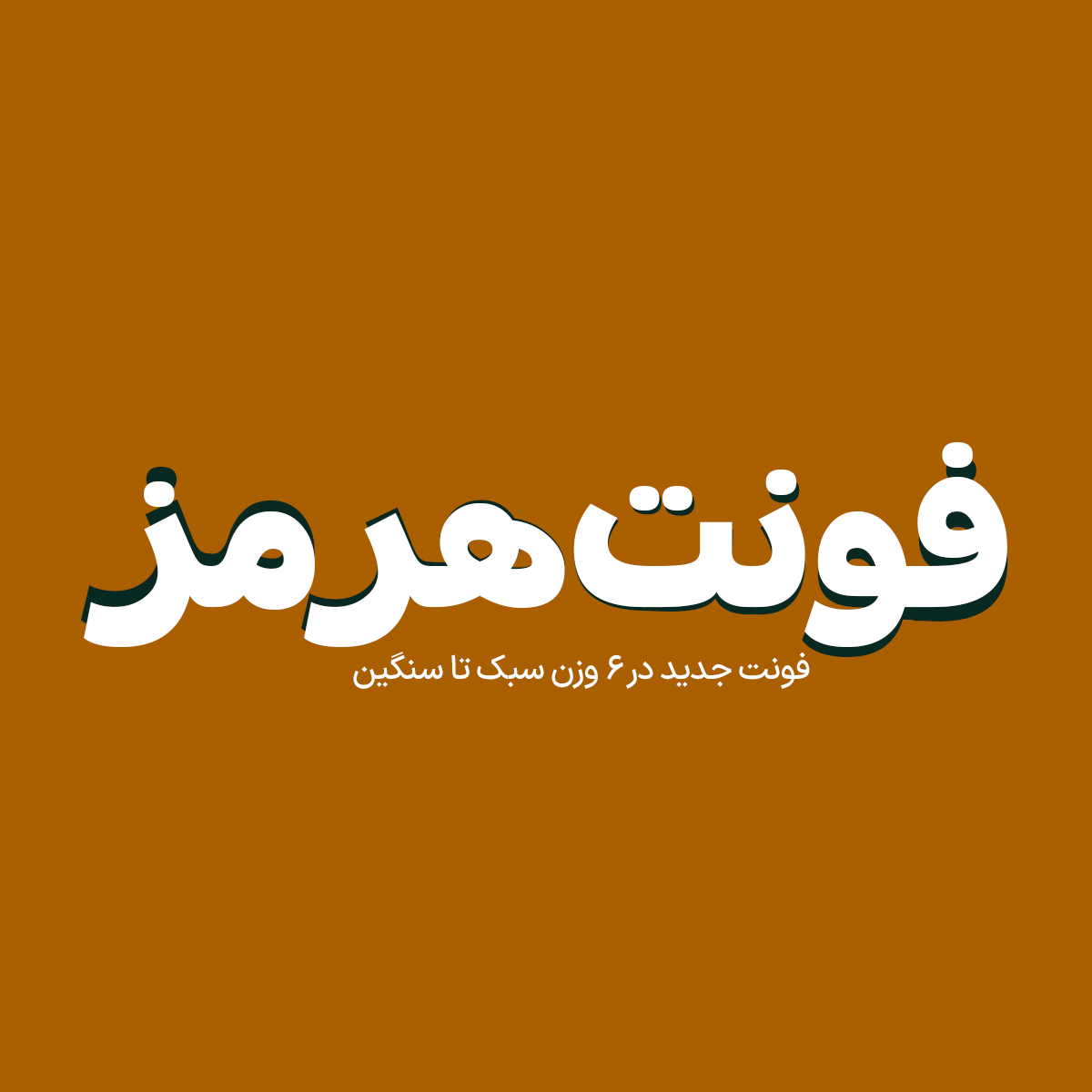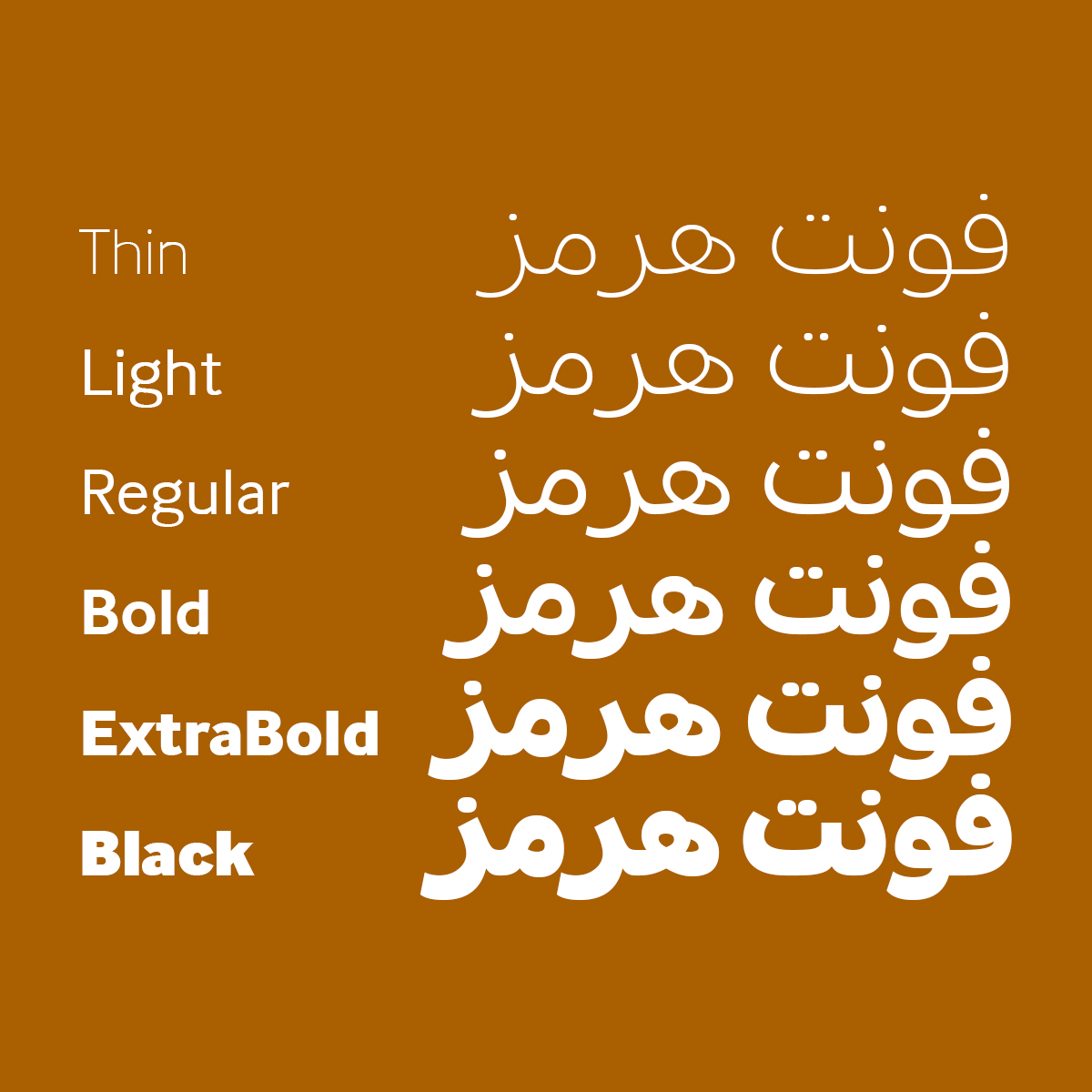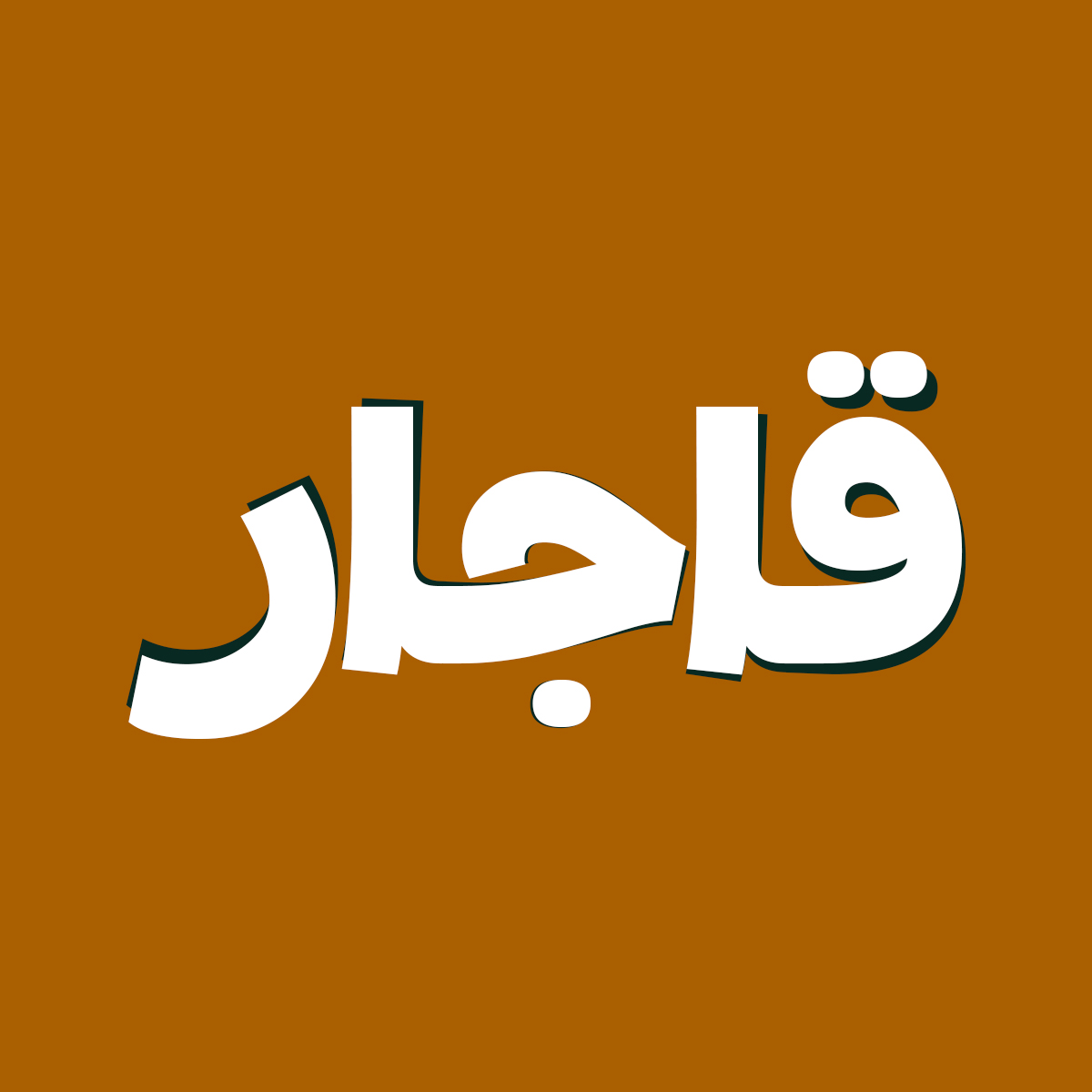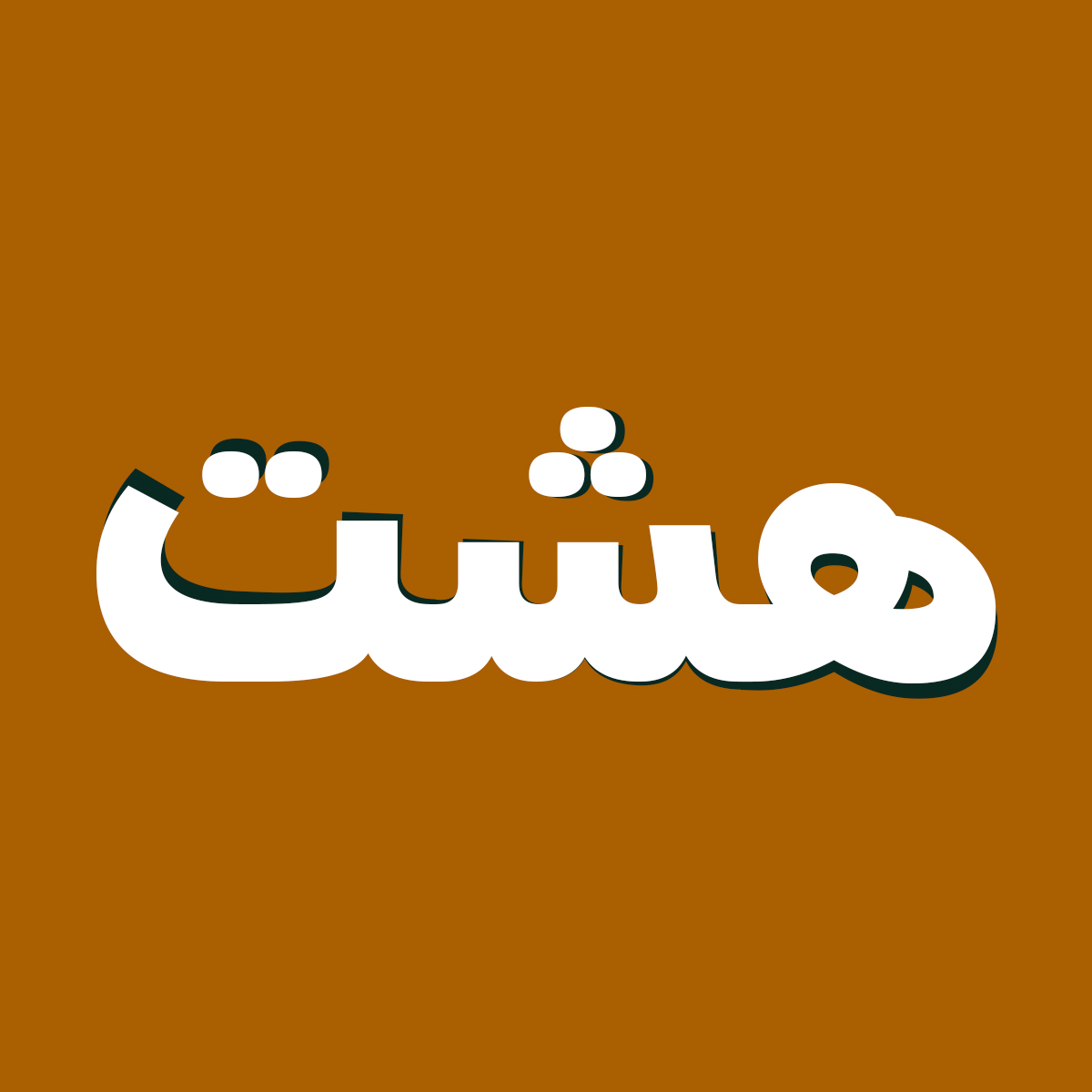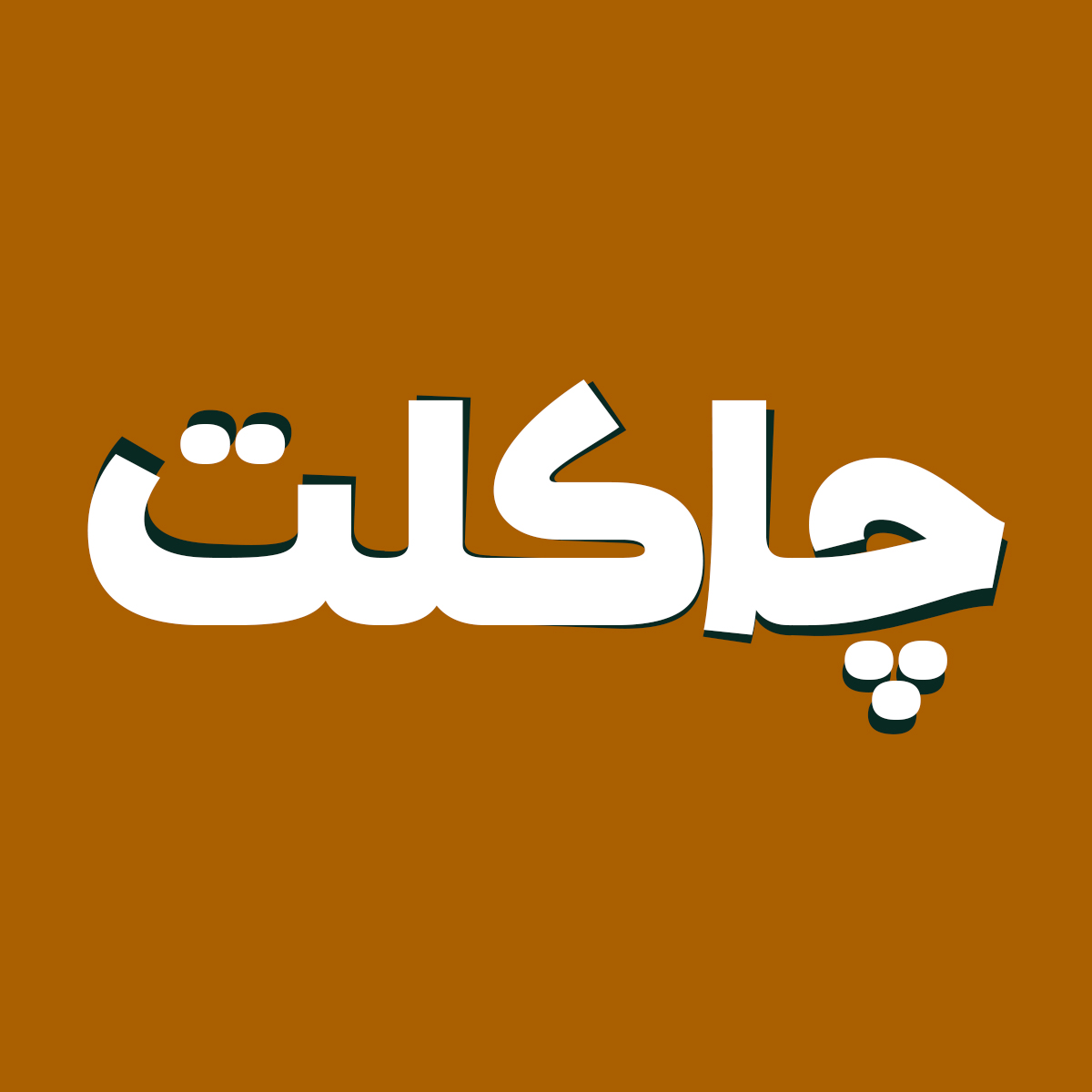
فونت فارسی هرمز Hormoz Font
اگر دنبال یک فونت فارسی با طراحی حرفهای، مدرن و منعطف هستید، فونت فارسی هرمز یکی از بهترین انتخابها برای شماست. این فونت با ظاهر چشمنواز،…
اگر دنبال یک فونت فارسی با طراحی حرفهای، مدرن و منعطف هستید، فونت فارسی هرمز یکی از بهترین انتخابها برای شماست. این فونت با ظاهر چشمنواز، ترکیب سنت و مدرنیته را به زیبایی در خود جای داده و در 6 وزن مختلف طراحی و منتشر شده است. در ادامه برای شما نمونه تایپ های این محصول حرفه ای رو آماده کردیم که میتونید مشاهده کنید.
پیشنمایش و نمونه تایپ های فونت هرمز
فونت فارسی هرمز Hormoz Font